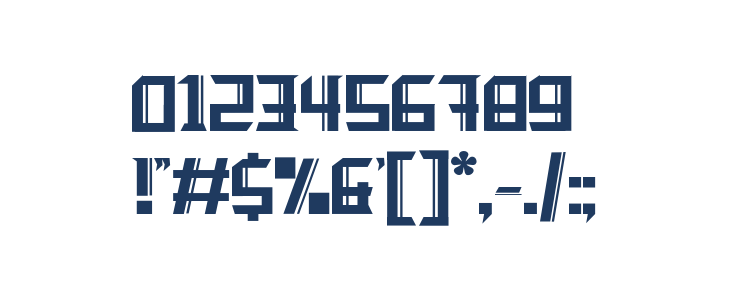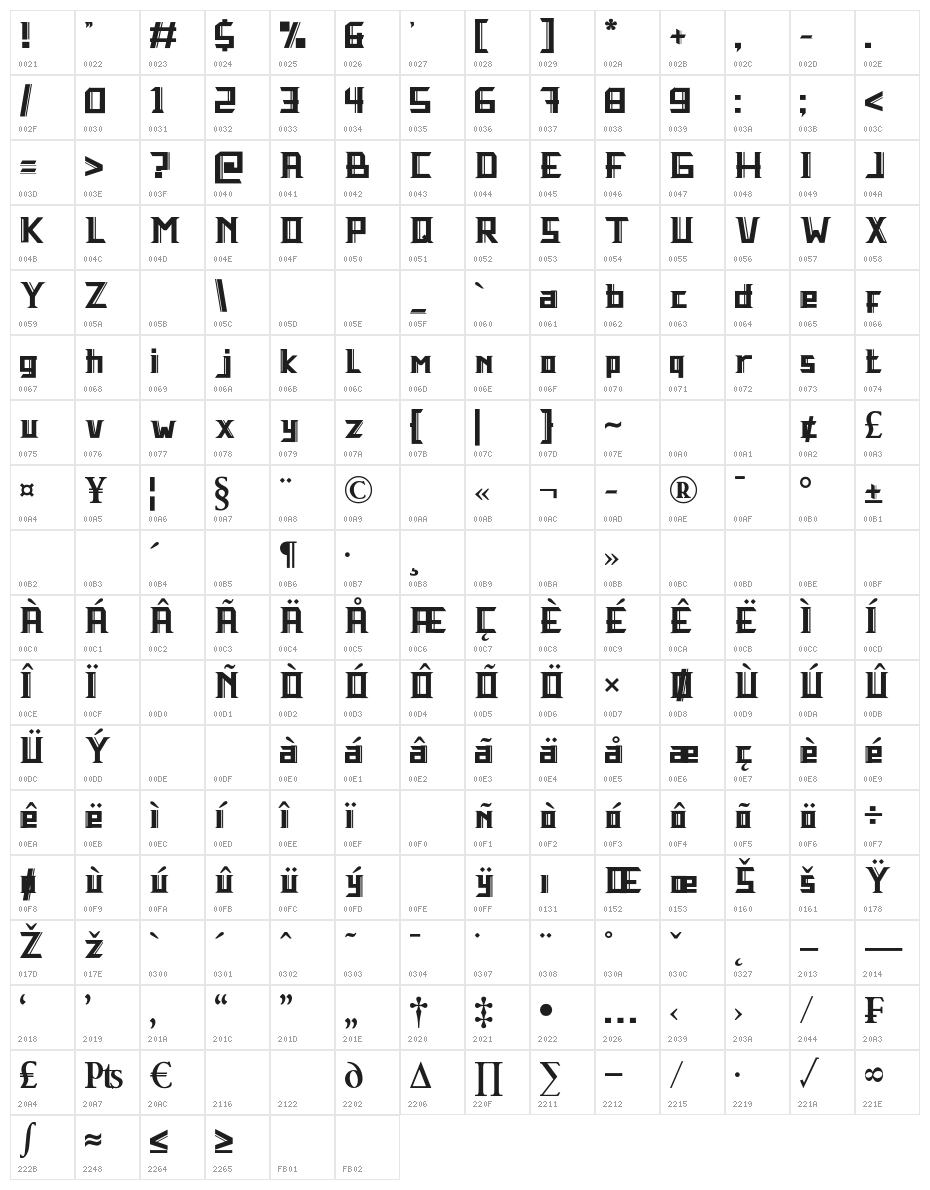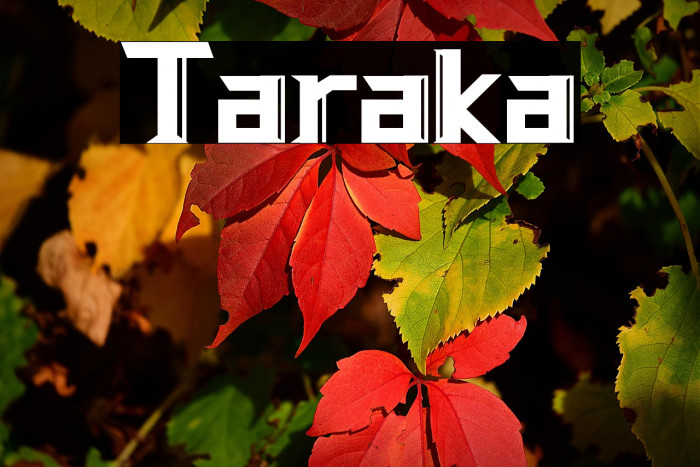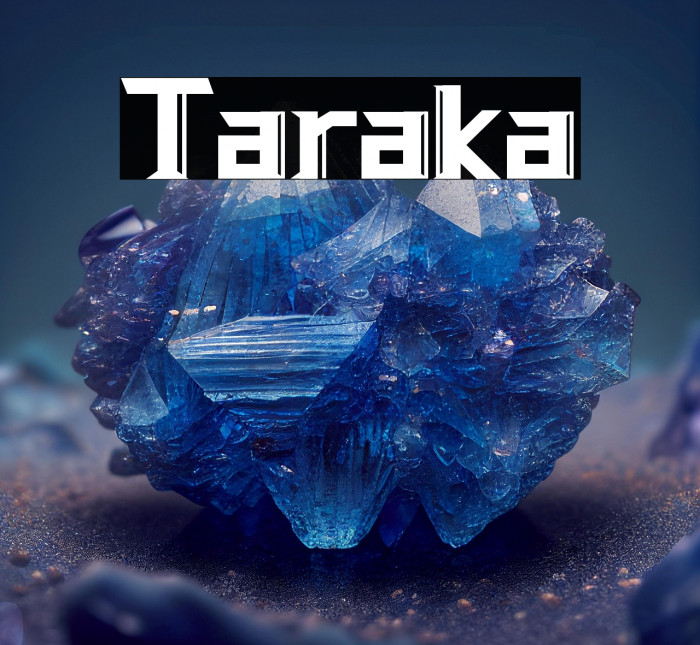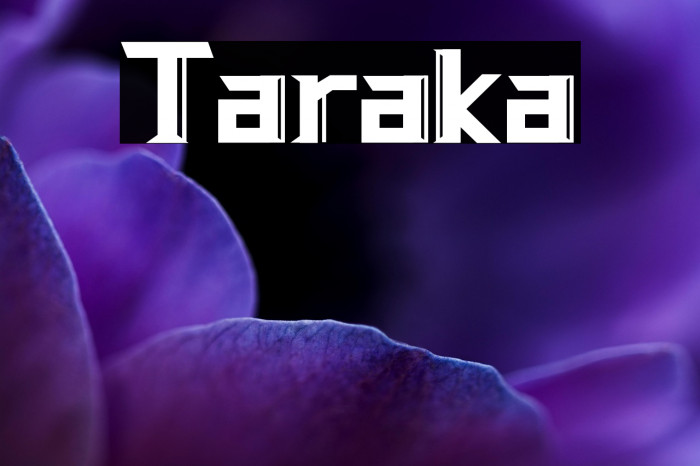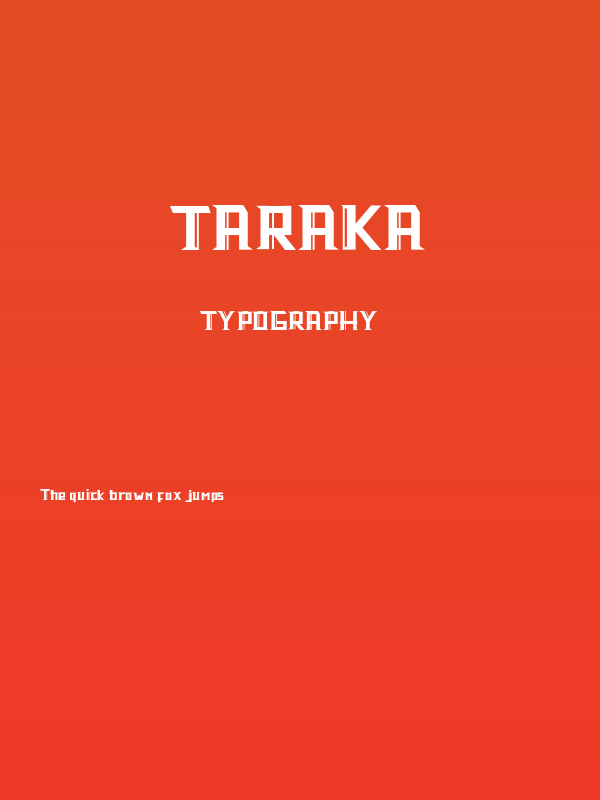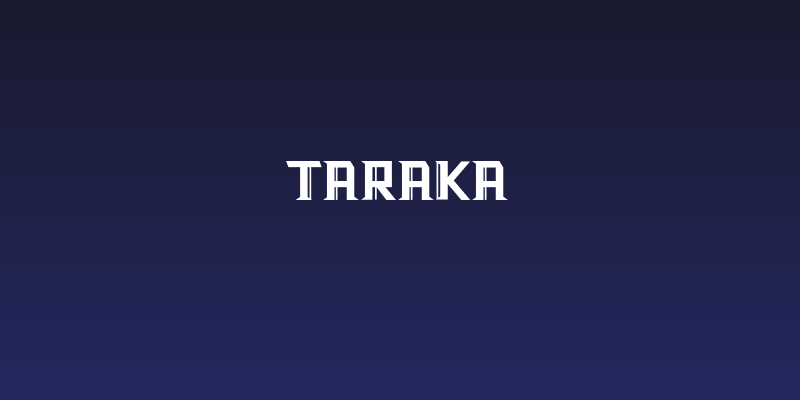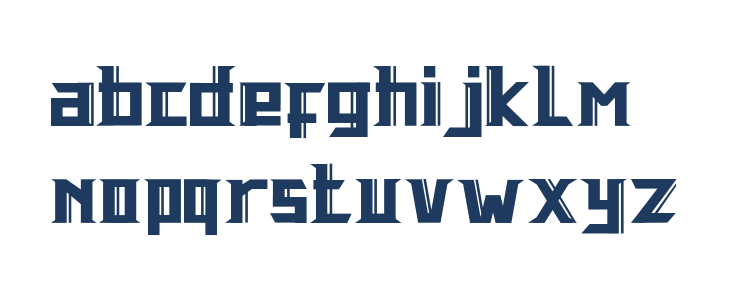
Taraka Font
| الاسم | Taraka |
| الفئات | Futuristic |
| مشاريع مقترحة | Ideal for sci-fi themed designs, video game titles, posters, and branding that requires a modern and edgy appearance. |